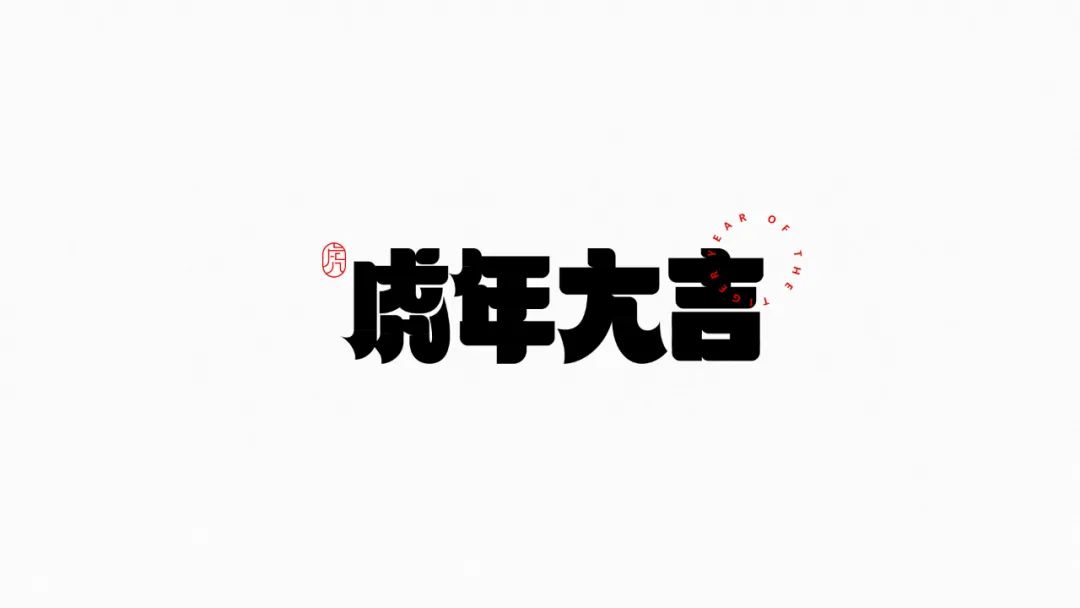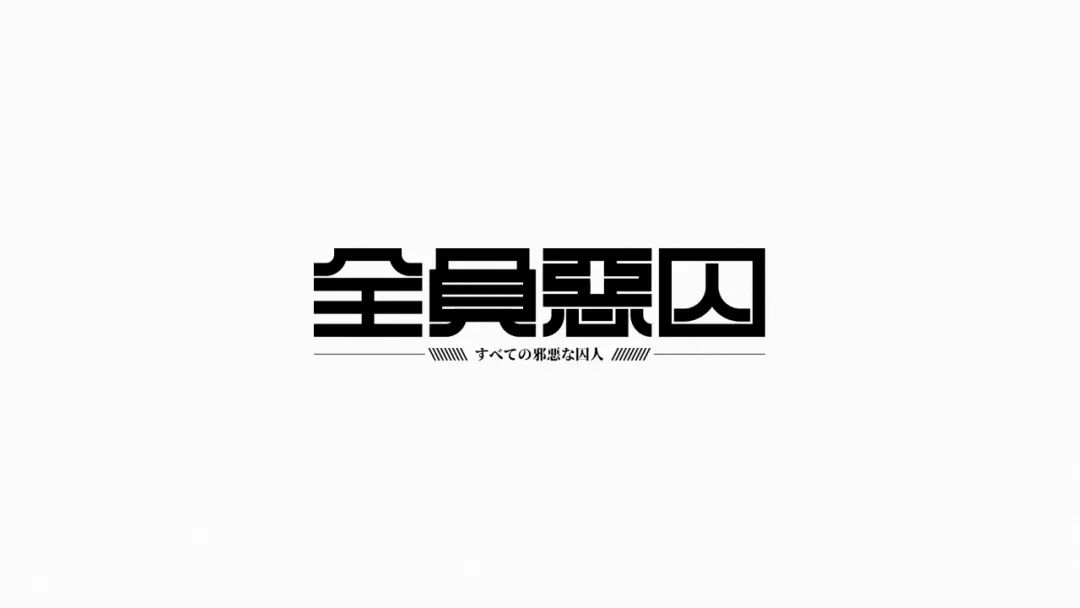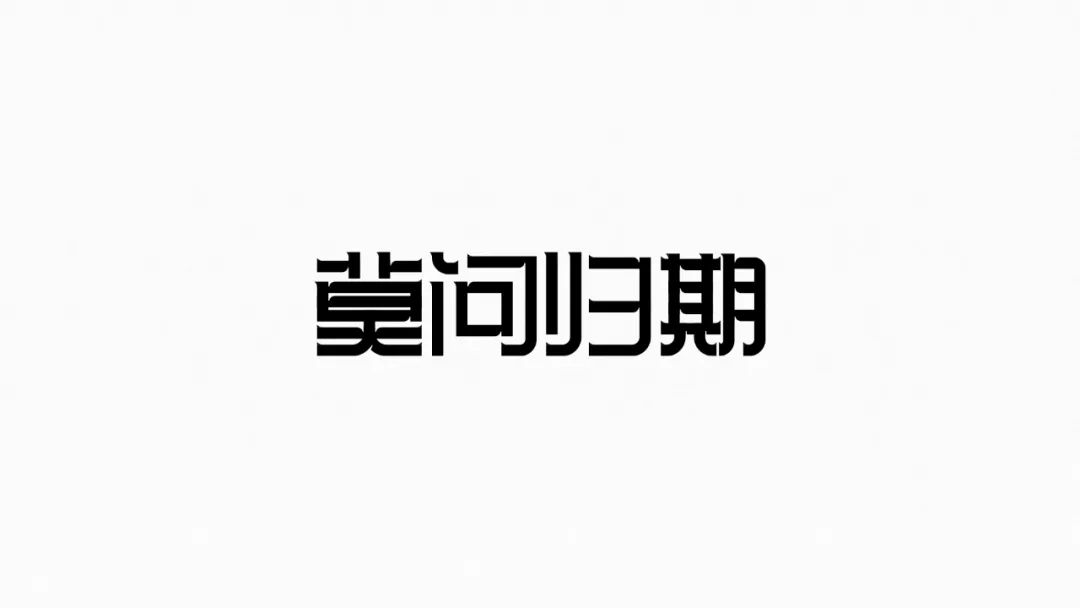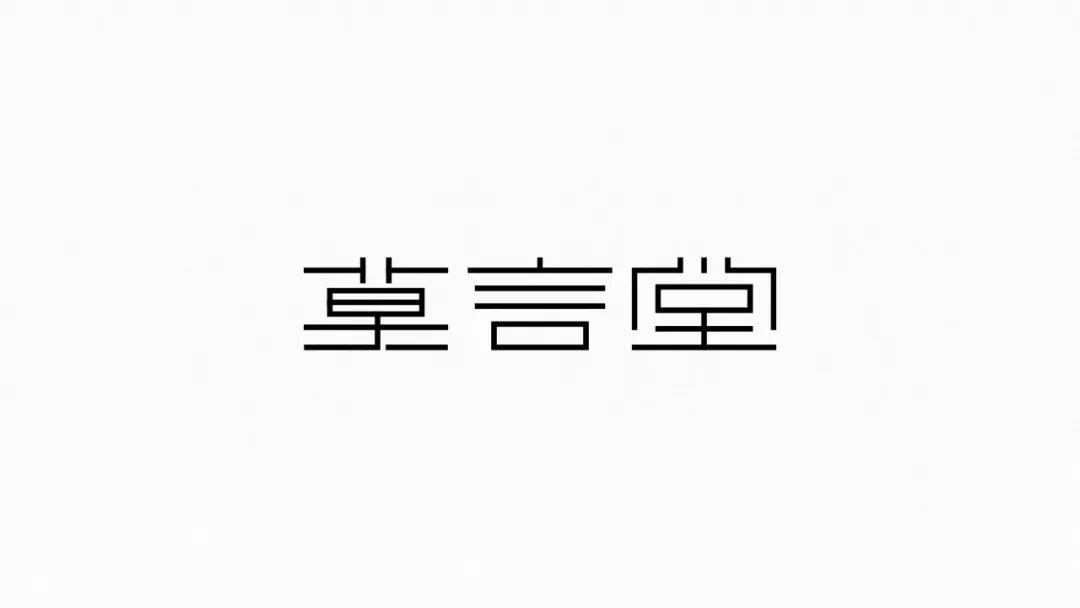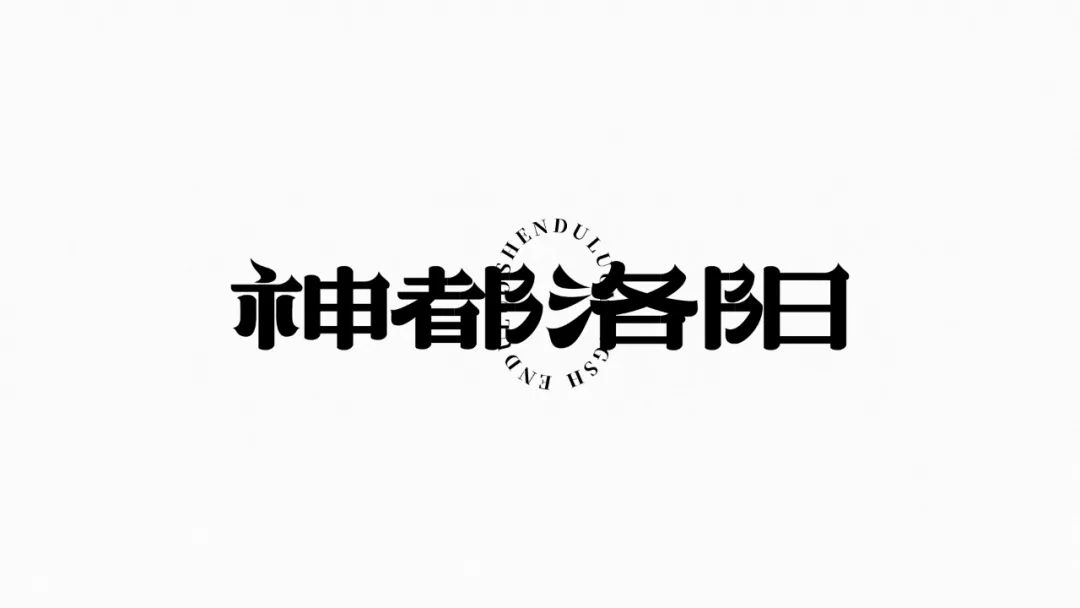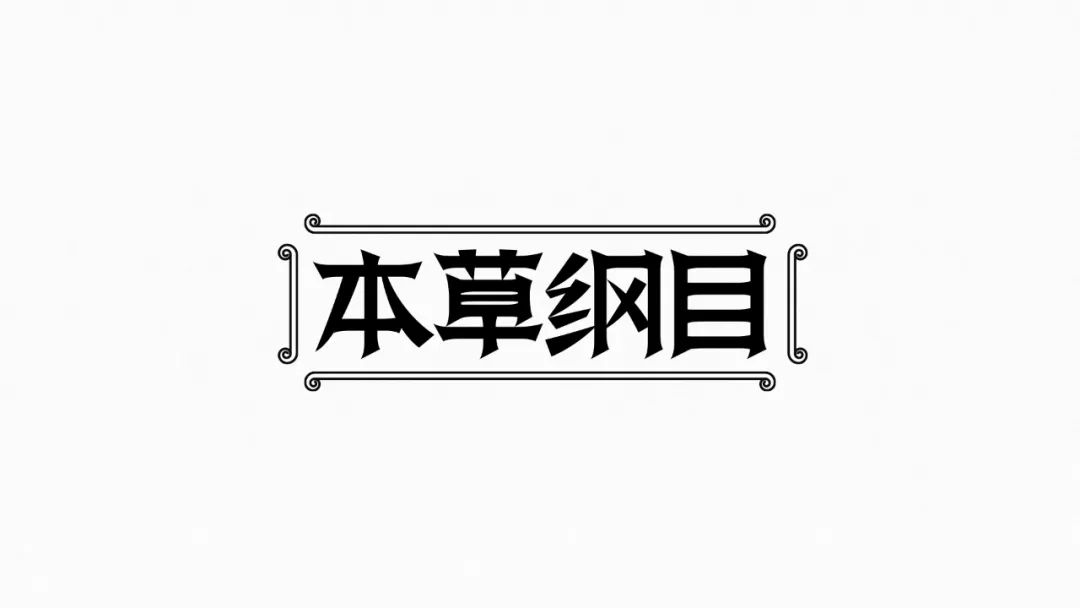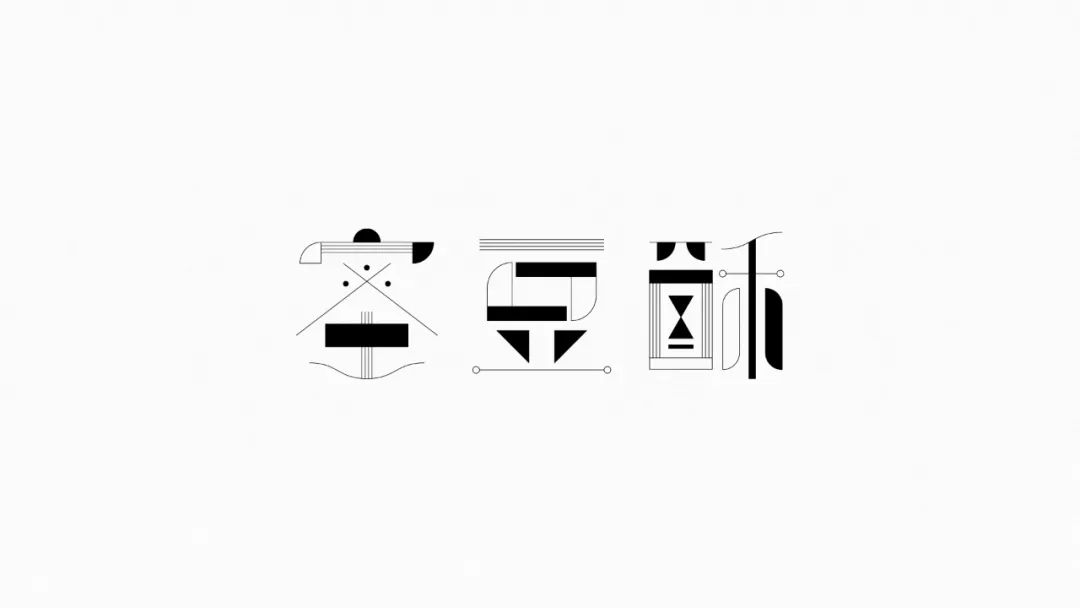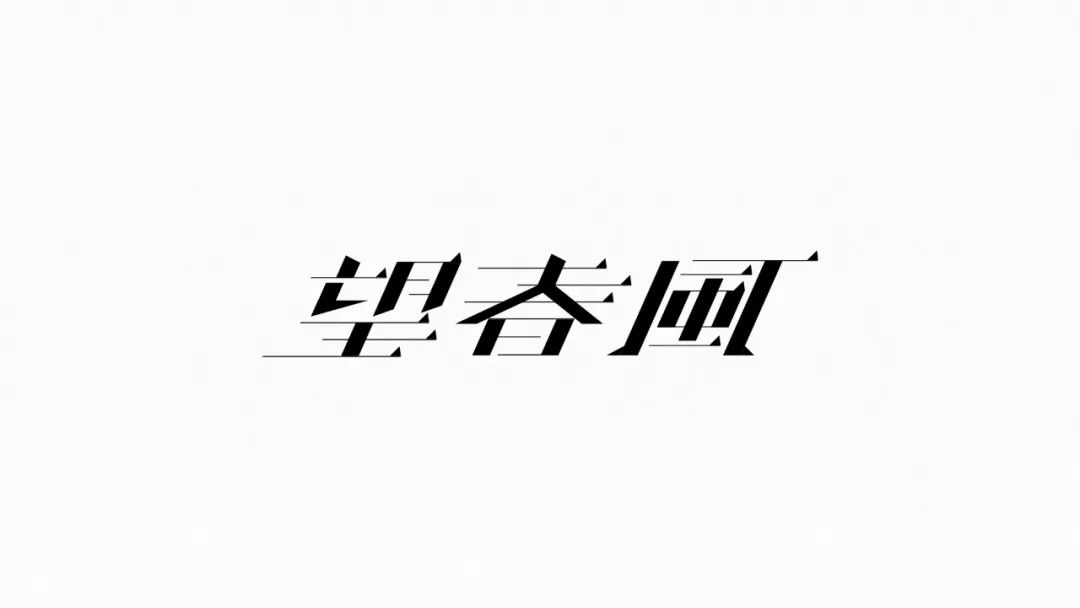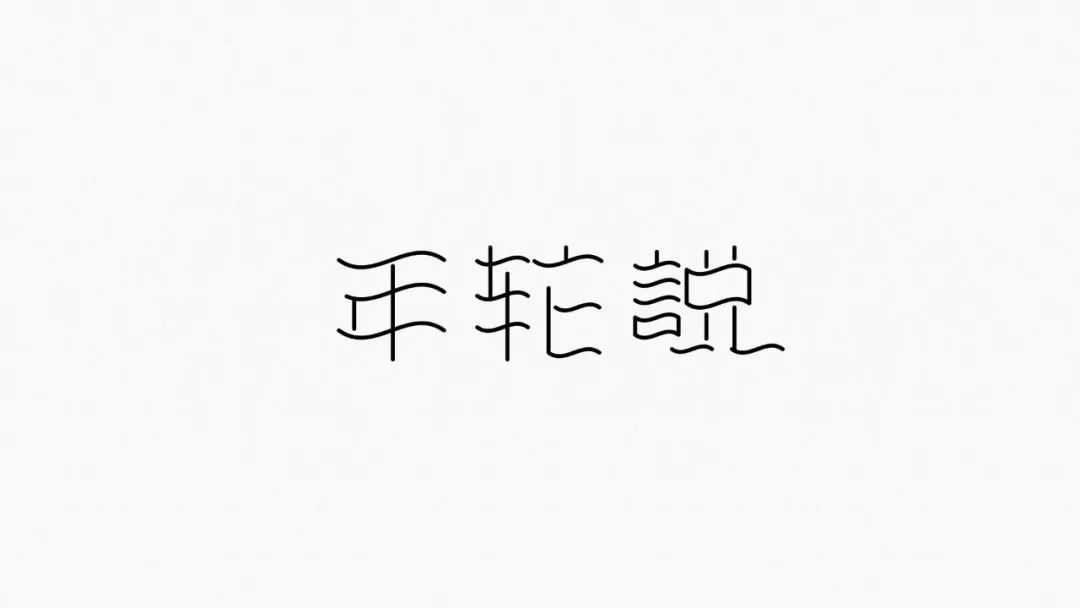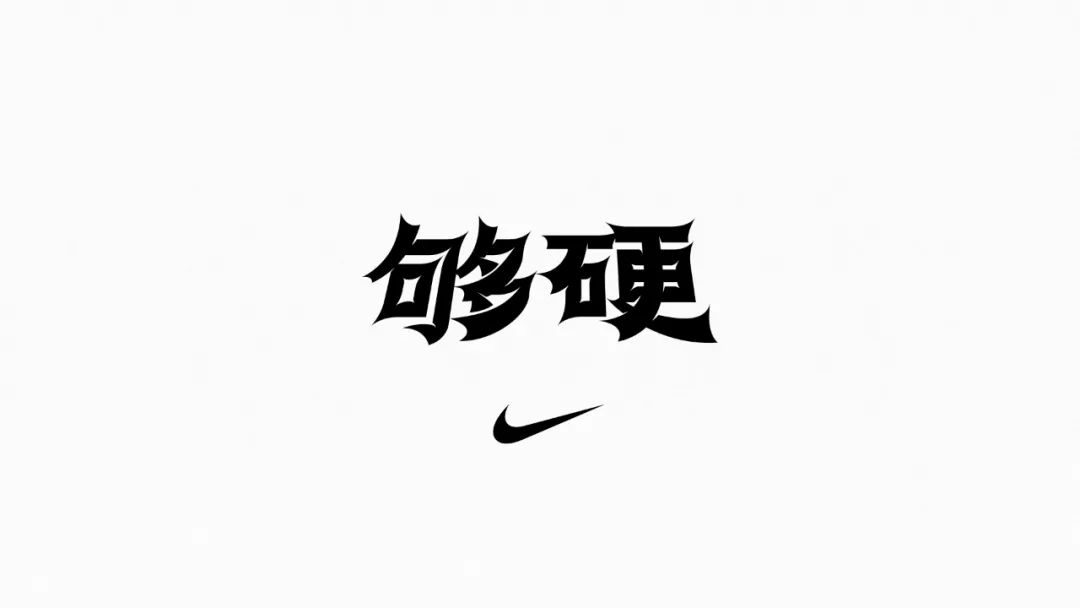
各种不同风格的字体造型和衬线的字体设计作品
这是他一组近期的字体设计作品,尝试各种风格的字体造型和衬线,对于书写方式、笔划结构有了更深刻的理解。看过越来越多优秀的字体作品,更觉才疏学浅。字体这种艺术形式,需要依靠大量的阅览和练习。
接下来,一起来看看其作品,一共28张。
字体设计的重要性相信大家已有了解,而随着大众审美的不断提高,大家对设计感的追求变得不可或缺,使得“字体”在视觉传达设计中有了一个必要存在的趋势。希望大家在2022年继续钻研字体设计并将其应用到实际工作当中。